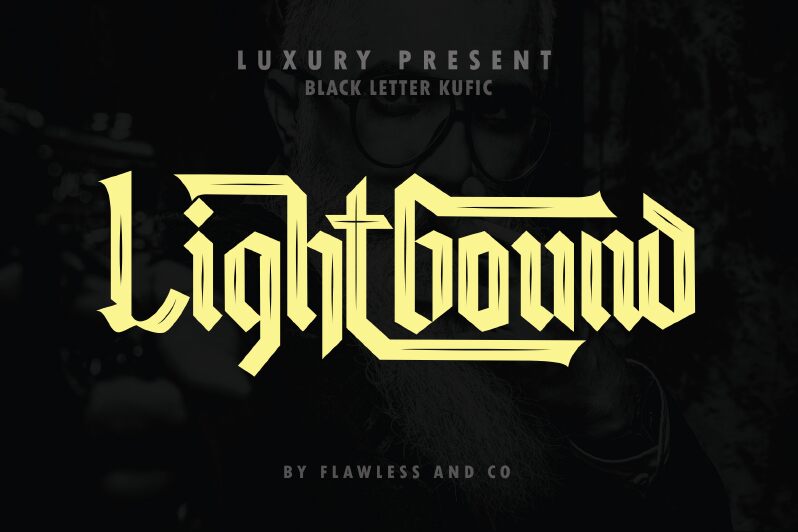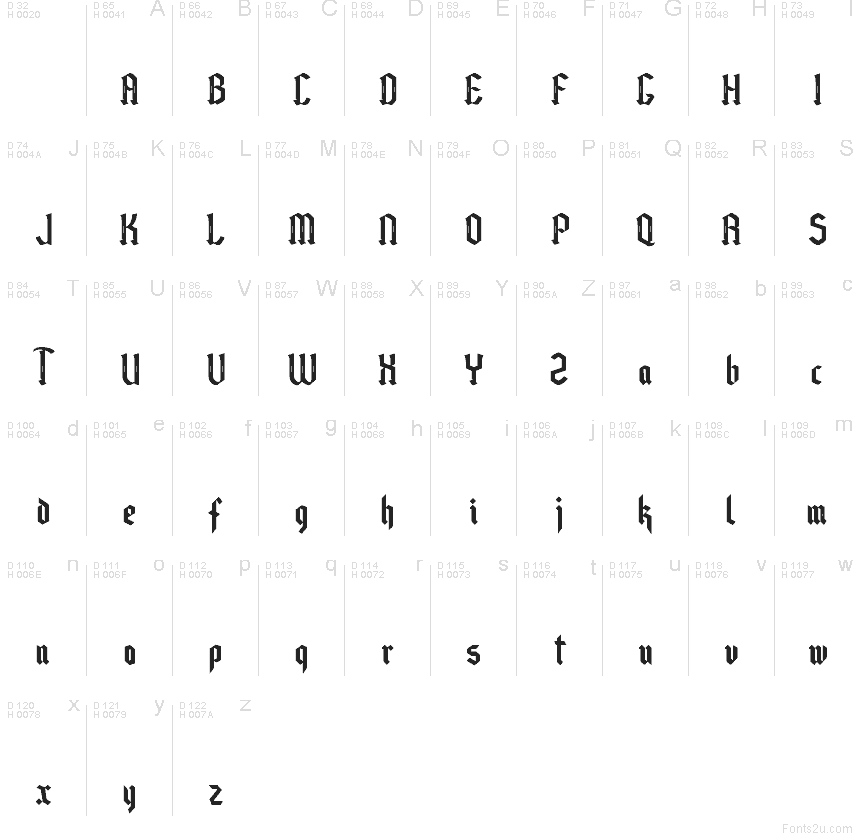
Lightbound od Flawless And Co je moderní bezplatné gotické písmo s výrazným „blackletter“ nádechem a nápadně odlehčeným stylem. Písmena sází na ostré spoje, dělené tahy a zúžené úhly, ale celkově působí čistším a méně starožitným dojmem než tradiční středověké návraty.
Hodí se pro titulky plakátů, obaly hudebních alb, streetwearový branding, obálky knih a redakční nadpisy, kde chcete gotickou energii bez hustých ornamentů. Jako bezplatné písmo se také skvěle hodí pro krátké nadpisy, skici log a titulní karty, protože jeho ostře řezané tvary dodávají i krátkému slovu tvrdou, nezaměnitelnou siluetu.